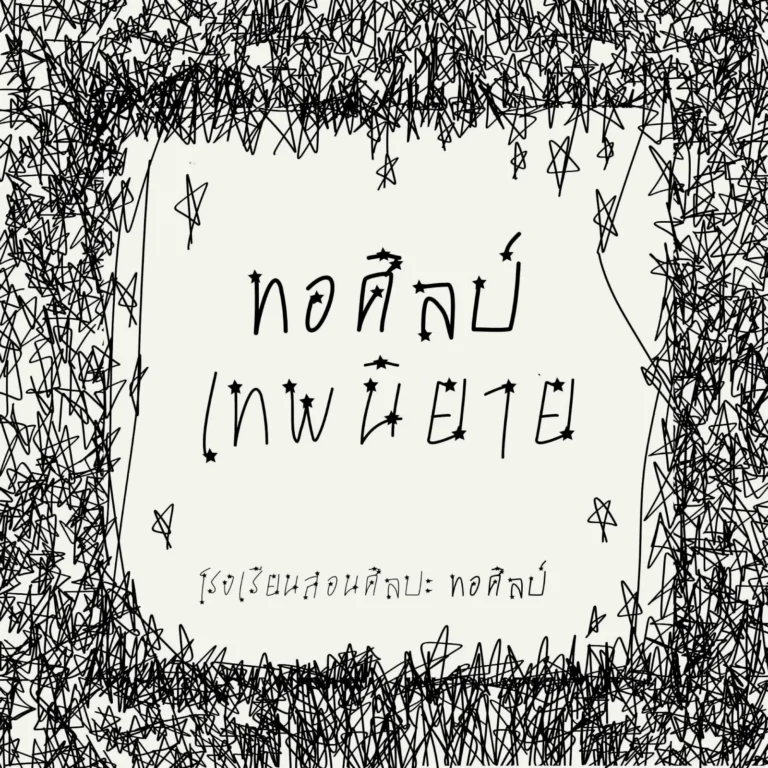
ทอศิลป์ เทพนิยาย (Torsilp Thepniyai)
ฟอนต์ “ทอศิลป์ เทพนิยาย” – เป็นฟอนต์ลายมืออีกตัวนึง จัดวางแบบจังหวะขึ้นๆ ลงๆ เก๋ๆ เป็นธรรมชาติประดับดาวไว้ตามจุดต่างๆ ฟอนต์นี้เป็นการนำฟอนต์ “ทอศิลป์ คิดถึงเธอ” มาต่อยอด